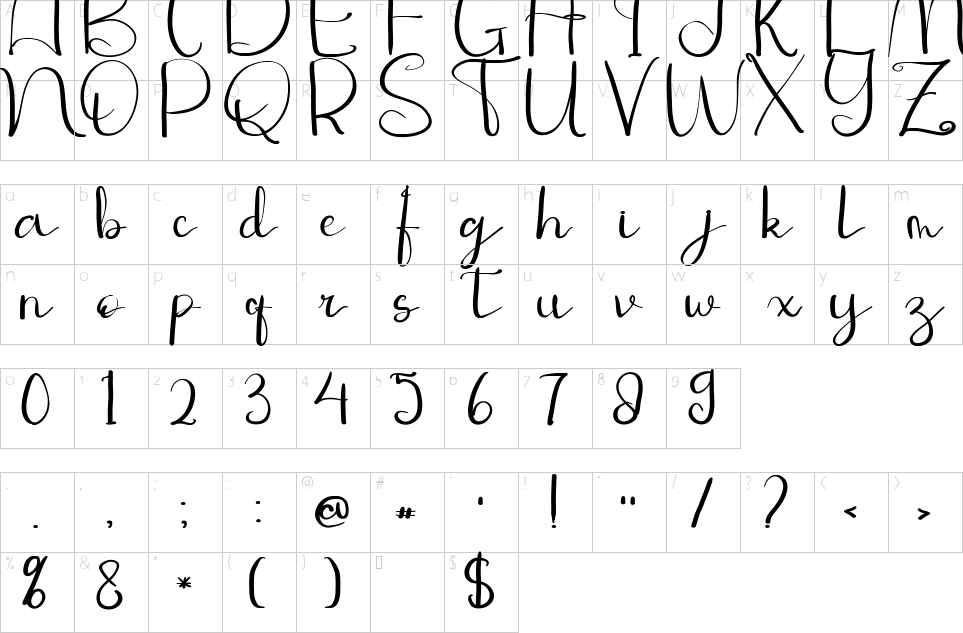
Antaro Awak Font
Descubra Antaro Awak Font, uma elegante e sofisticada opção para seus projetos digitais. Desenvolvida pelo designer Canden Meutuah, Antaro Awak traz um ar de sofisticação que se combina perfeitamente com as necessidades de diversos projetos, desde identidades visuais até design de letras. Este é o seu momento para experimentar a beleza de Antaro Awak. Desenvolvida para atender tanto os criativos de desktop como os de computador, esta fonte oferece uma variedade de características que tornam seu trabalho de design mais gratificante e produtivo. Com 621 downloads desde sua criação, Antaro Awak não apenas se destacou no mundo da design gráfico, mas também se destacou pelo seu design único e personalizado. Descubra o poder de Antaro Awak para trazer a sua marca à vida.
Mapa de caracteres da fonte Antaro Awak Font